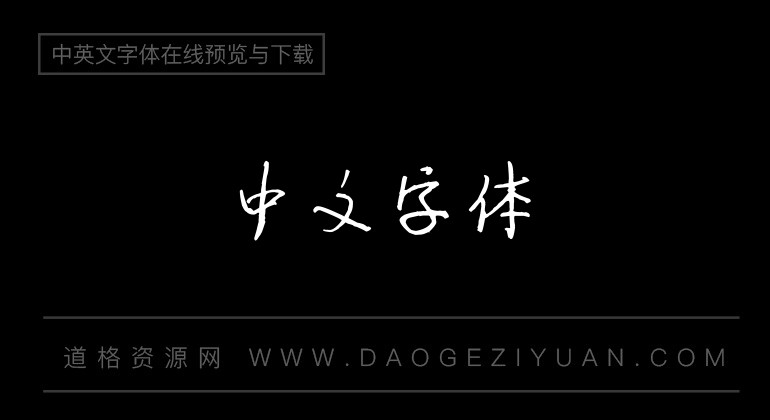
逐浪硬行体
逐浪硬行体是一款极简主义风格的中文字体,由中国著名设计师黄洪创作,于2015年发布。它具有清新明快的视觉效果,拥有极简的线条,以及清晰的结构和锐利的笔画,令人印象深刻。这款字体支持简体中文和繁体中文,可以应用于各种不同的场合,如印刷品、广告、网页、标识和标牌等。
逐浪硬行体是一款非常不错的手写艺术字体,具有很好的视觉感,适合于文化类的宣传设计、商业类品牌的广告和产品包装设计以及个性化文字排版等较多场景。